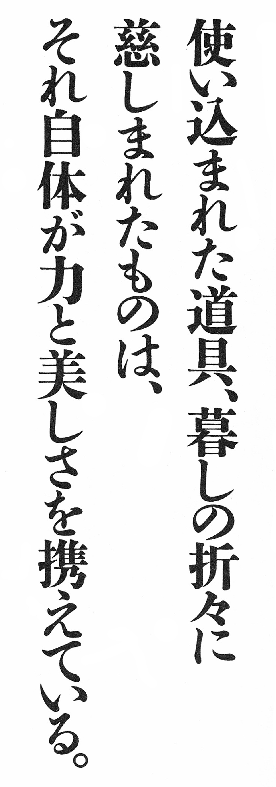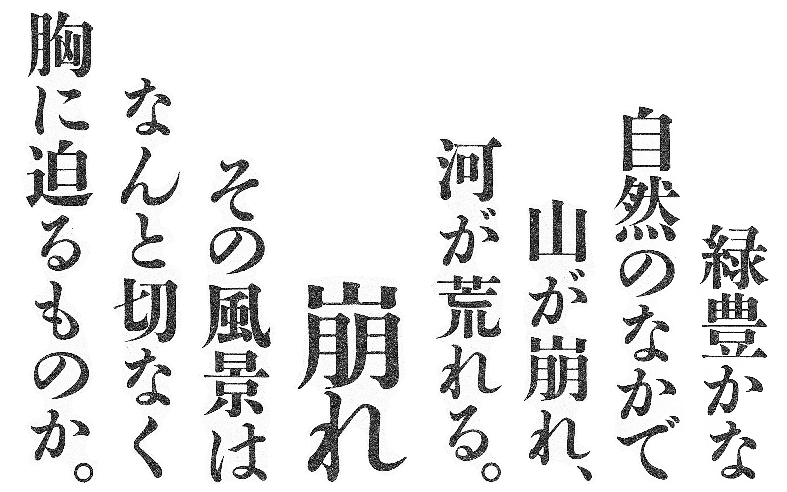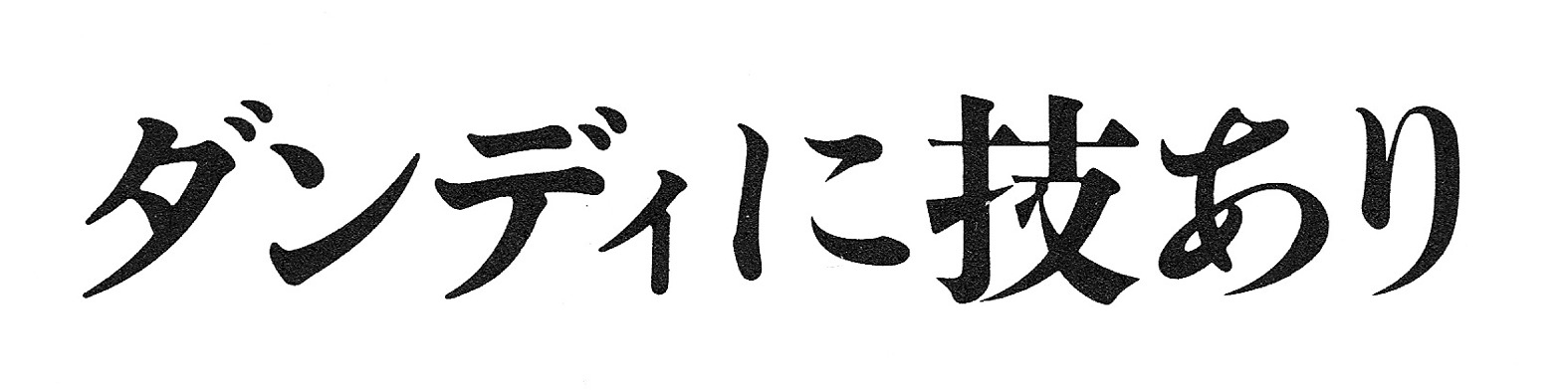
秀英初号明朝
パソコンや携帯電話の画面の明るさとはまったくちがう。
ガラスの文字盤は、身体を通り抜けてしまいそうに深くやわらかい光を放っていて、それをみていたら、私は蛍を思いだした。
不思議だなあ。この光が、文字になるなんて。
先月、大阪で、動く写真植字機をみせていただいた。そんな日がくるとは思っていなかった。
子供のころ、印刷物の文字がどうやってできているのかは大きな謎だった。外国の映画にでてくるようなタイプライターはイメージしやすかったが、キーボードを打つことと、それが文字になることとの間には、どうしても理解できない空白の溝があった(文字化け、なんて言葉は当時、存在していなかった)。
そんなある日、父がMacコンピュータを買ってきた。中学に入って間もないころだ。
薄暗いモニター画面に映しだされた文字を印刷してみると、画面上ではがたがたにみえていたものが、びっくりするほど滑らかになって、自分がかいた文章でも、ちょっと立派にみえることがうれしかった。
文字の印象の違いが「フォント」と呼ばれるもので、それぞれに名前があることも、パソコンのつかいかたを教わってはじめて知った。本をつくることは、きっとこの延長線上にある。そう確信した。
しかし、どんなに「フォント」を探しても、いつも本や雑誌でみている文字は見当たらない。これはいったいどういうわけなのだろう。
そのとき、私が苦しまぎれに考えたことは、父のパソコンと、本をつくるためのパソコンは、きっと階級が違うのだろう、ということだった。高名な音楽家が庶民には手の届かないヴァイオリンをもっているみたいに、そしてその音を聴きたいためにコンサートへ足を運ぶ観客がいるように、文字にもきっと家庭用とプロ用があるのだろう、と。そんなふうに思ってしまうくらい、同じ印刷された文字でも、その印象は決定的に違っていた。
空白が埋まったのではない。
いつの間にか気づかないふりをしていただけだ。
黄緑色に浮かびあがった文字をみながら、そんなことを思った。
「単純な機械なんです」
手動の写真植字機が現役だったのはずいぶん昔のことなのに、すべて体にしみこんでいるという手つきで、すいすいとレバーを操りながら、職人の方が笑って言う。
「でも、ものすごく、うまくできている機械です。こんなんよう考えたなあと思います」
業務用のミシンを巨大にしたような、見映えのしない無骨な機械なのに、ライトがつき、文字盤が照らされたとたん俄に、潜水艦のコックピットさながらの風情が漂う。
大きな印画紙を暗箱にセットし、歯車を調節し、レンズをあわせる。ガシャン、ガシャン、という心地いい確実な音で、文字盤から選んだ文字を印画紙に焼きつけていく。
何の文字を打っているのかはまわりからみえないのに、つい無言になって、手の動きに見入ってしまう。シャッターを切る音だけが響く静寂のなかで、そこには空白がないようにみえた。
学生時代、古本漁りに精をだしていたころ、たまたま見つけた『ダンディに技あり』という本で、「写植印字(カバー・扉・帯) 前田成明」というクレジットをみた。そのひとの名前は、「ブックデザイン 日下潤一」と「イラストレーション 大橋歩」のあいだに堂々と並んでいた。
シャショク?
私は首をかしげ、改めて、表紙の文字をまじまじとみた。
「印字」の意味は想像がついたが、「写植」の方は、聞いたことのない言葉だった。もしかして、今までみていたのもずっと、パソコンのフォントじゃなかったのか。
それは私にとって、長年の前提を大きく覆す新事実だったけれど、ああ、やっぱり、というか、自分が思ったほどは衝撃をうけなかった。
そのときにみた文字が、〈秀英初号明朝〉(写研の秀英明朝/SHM)であったことも、心の動きに影響していたかもしれない。
いかにもプロ仕様の、しなやかで、きらめくような文字の印象から、文字を「植える」ひとというより、活きのいい魚をつかまえてきたひとみたいに思えたのだ。
〈秀英初号明朝〉は、長い伝統のある秀英体のなかでも、明治末期、なんと今から100年も前に誕生した「秀英体初号活字」がもとになっている。古いから模範的で型にはまっていると思うのは早計で、その線やかたちはまさに自由闊達。筆の勢いにのって勢いよく跳ねたり、翻したり、そうかと思えば、海の底でじっとしているような目立たない字もあるのがおもしろい。
それが写植でもつかわれるようになったのは1981年のことだ。
デザイン書体のブームで写真植字が飛躍的に普及し、その影響で本物の「活字」が第一線から姿を消しつつあったころ、この書体に強い愛着を持っていたデザイナーの杉浦康平が熱望したことによって写植化が実現したという。
今は完全にDTPに取って代わられている写真植字が、かつては革新的な技術で活版印刷を脅かし、その衰退を早めた存在であったことは皮肉だけれど、デザイナーのプロ意識というより人間の業を感じさせるこのエピソードには心打たれる。
だって、日本語の文化を守るためとか、他人のデザインと差をつけるためとか、そういう理由では納得がいかない。ほんとうは、その書体で組まれたところを自分がみたい、という、きわめて純粋で、自己中心的な感情だったはずだ、と、私は思っている。
「この書体でなければだめだ」と思うことの、人間らしさ。説明のつかなさ。
それに第一、杉浦康平が優れた文字の使い手でなかったら、印刷会社や書体メーカーを動かすことはできなかった。
そのころ、文字にこだわりをもつデザイナーは、自分の好みに文字を組んでもらえる腕のいい職人を直接指名することがめずらしくなかったそうだ。前田成明さんという方も、写植の時代に多くの名デザイナーを支え、活躍されたオペレーターのひとりである。
〈秀英初号明朝〉は、デザイナーの根強い支持を受けて数年前にデジタルフォント化され、デザイナー自身がパソコンでつかえる書体になった。もちろんタダではないとはいえ、趣味の延長でこの書体をつかいたいと思えば誰にでも手に入るのだから良い世の中になったものだが、見方を変えれば、家庭用とプロ用の区別が次第になくなりつつあるともいえる。
その変化が何をもたらすのか、私にはわからない。
でも、個人でつかうという選択肢が現実的になって、はじめてはっきりとわかったことがある。
私は書体を「モノ」として所有したいわけではないということ。
この文字でかかれた言葉に感じる、神秘性や、敬意や、畏れの背後にある物語を大切にしたい。
美しい文字を生かすには、それに見合う強い心が求められるのだ。